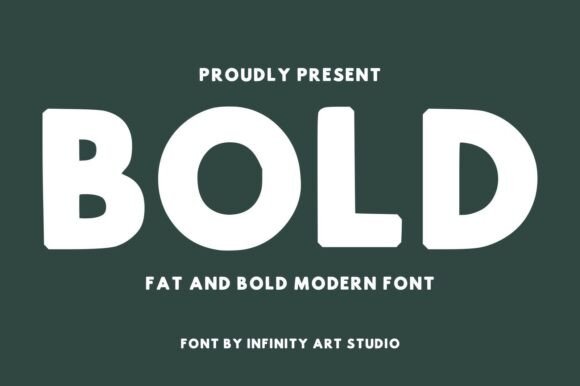
Bold
Bold – Revue détaillée du police d’affichage moderne
Bold Fat Modern Display Font se démarque comme une police à la fois puissante et épurée. Conçue avec des caractères épais et audacieux, elle crée un impact visuel immédiat qui capte l’attention sur n’importe quel support. Que vous soyez graphiste, chargé de branding ou créateur de contenu, Bold offre le style contemporain et confiant dont vous avez besoin pour faire ressortir vos projets.
Pourquoi choisir Bold pour vos créations ?
- Impact visuel maximal : les traits épais garantissent une lisibilité exceptionnelle même à distance.
- Style moderne et minimaliste : parfait pour les tendances actuelles du design minimal.
- Polyvalence : idéal pour les titres, logos, affiches, emballages, graphismes réseaux sociaux et t‑shirts.
- Confiance et contemporanéité : transmet instantanément une image de marque forte et actuelle.
Utilisations recommandées
- Headlines percutantes pour sites web et blogs
- Branding et logos d’entreprise
- Affiches publicitaires et flyers
- Visuels pour Instagram, TikTok et autres réseaux sociaux
- Packaging de produits et étiquettes
- Design de t‑shirts et merchandising
Points forts de Bold
- Lisibilité optimale même en petites tailles grâce à des formes bien définies.
Conclusion – Le choix audacieux pour vos projets créatifs
Bold est plus qu’une simple police : c’est une déclaration de style. Son design robuste et minimaliste le rend incontournable pour tous les créateurs cherchant à ajouter une touche de puissance visuelle à leurs travaux. Téléchargez Bold dès aujourd’hui et donnez à votre communication le look confiant et contemporain qui fera la différence.